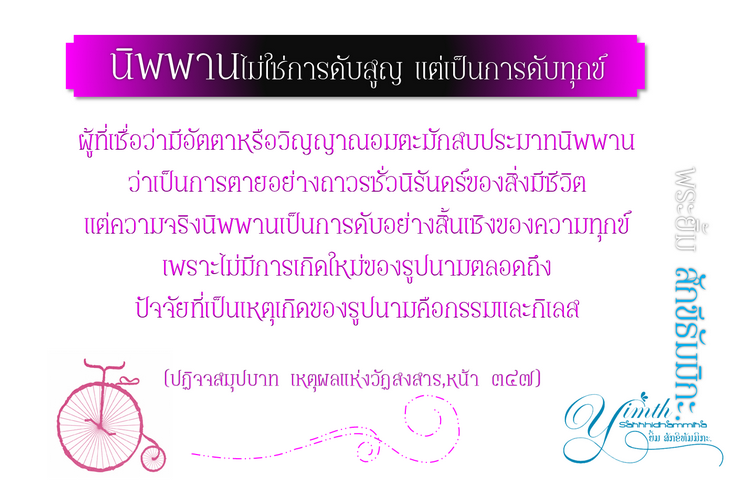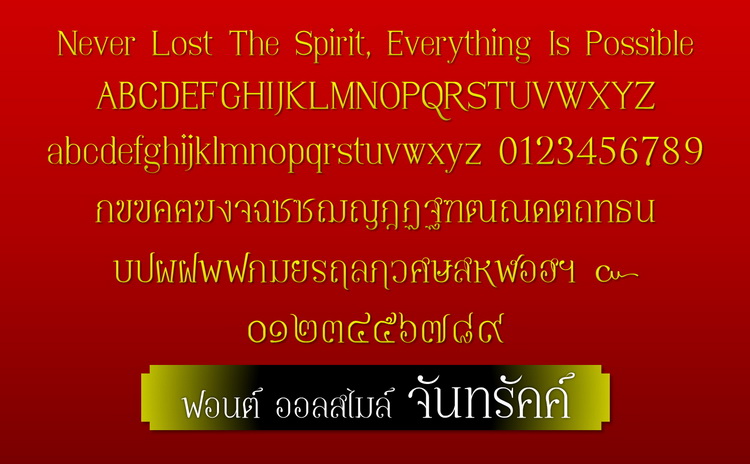
Alsmile Golden Class
:12: ว่ากันตามเนื้อผ้าครับ
:12: กระจ่างขึ้นอีกครั้ง นี่ละคือสิ่งที่อยากรู้และอยากฟัง
ตอนนี้คือศึกษาในเรื่องเหล่านี้อยู่นะครับ หลวงพี่ยังไม่ได้ทำงาน
เรื่องการทำฟอนต์ ณ จุดปัจจุบันนี้คือแค่ระดับฝึกและลองศึกษาเรียนรู้เท่านั้นนะครับ
เพราะฉะนั้นข้อคิดเห็นต่าง ๆ เหล่านี้ล้วนมีประโยชน์เมื่อได้ทำงานจริง
ผิดพลาดก็อยากให้ชี้แนะแบบนี้แหละดีสุด หลวงพี่ไม่ได้อยู่ในสายนี้โดยตรงก็อยากฟังความคิดเห็นบ้าง
อย่างทีแรกที่ถูกถามว่า หลวงพี่ทำมาหลายตัวแล้ว น่าจะปล่อยให้ใช้เป็นธรรมทานบ้าง
ส่วนตัวก็คือไม่แน่ใจ เพราะหลวงพี่ทำเล่น ๆ ไม่ได้จริงจัง ฝึก ๆ ทำไป ท้ายที่สุดคือไม่ได้ยึดเป็นอาชีพอะไร
ส่วนใหญ่ก็คือทำไว้ใช้เอง ถ้าแจกก็คนที่สนิดกันจริง ๆ เท่านั้น น้อยนักคนอื่นจะได้ใช้ฟอนต์หลวงพี่
เรื่องความเข้าใจก็เรียนรู้จากแหล่งที่นี่ละครับ ตอนนี้ก็อิ่มตัวในเรื่องการออกแบบระดับหนึ่งแล้ว
สักพักก็คงเลิกทำ แล้วไปศึกษาเรื่องอื่น ๆ ต่อไป
สวยดี เ้หมาะักับละครเอ๊กแซ็กท์
ฟอนต์บนพื้นสีทองนั่น(ไม่รู้ฟอนต์อะไร) น่าเอาไปใช้ในละครเวทีเลย  :25:
ปรับปรุง แก้ไข พัฒนาให้ดูเข้ากันมากขึ้น
ฟอนต์นี้กำลังทำตัวหนา ยอมรับว่าเป็นตัวแรกที่ไม่ทำต่อเนื่องให้เสร็จลวดเดียวเหมือนที่ทำมา
ต้องพักเวลาเนื่องจากภาระอื่น ๆ
ตัวนี้ช่องไฟยังไม่สะอาดนะครับ
ลองปรับให้โปร่งตาอีกนิด เอ๊ะหรือหลวงพี่จัดแบบ Justify ครับ :09:
จัดแบบ Justify ใน Ms Power point ครับ  :52:
แหม ถ้าจะยังไงน่าลองจัดแบบธรรมดาๆ ก่อนนะครับ ถ้าอยากให้ช่วยกันวิชามน่ะจ้ะ
(เอ๊ะนี่บอกกี่รอบแล้วเนี่ย :30:)
:56: ทีแรกทำเล่นและใช้งานจริงของตน ไม่คิดเรื่องนี้ โต๊ษจ้า  :52:
นั่น จริงด้วย เดาไว้อยู่แล้วว่าฟอนต์นี้ต้องหายใจลำบากแน่เลย
แล้วก็ช่องไฟไม่ค่อยสม่ำเสมอจริงๆ ด้วยครับ
หลวงพี่ลองหรี่ตาแล้วสำรวจบางตัวที่เล่นลีลาจนแขนขามันไปตีกับตัวอื่นๆ ดูนะครับ มีเยอะเลย
ส่วนบางตัวที่โปร่งๆ แล้วอันนั้นดูพอดีแล้ว (ดูคำว่าปัญญา) เนี่ยถ้าได้ความลื่นตาระดับนี้ผมว่าเวิร์กครับ
ขอบคุณครับ เดี๋ยวจะไปปรับให้หายใจได้โล่งสะดวกขึ้น
เก่งและขยันมากเลยครับ
ฟอนต์นี้มาสเตอร์พีสจริงๆ  :12:
กว่าผมจะผลิตแต่ละชิ้นออกมากได้นี่ เอาเรื่องเหมือนกัน  :08: